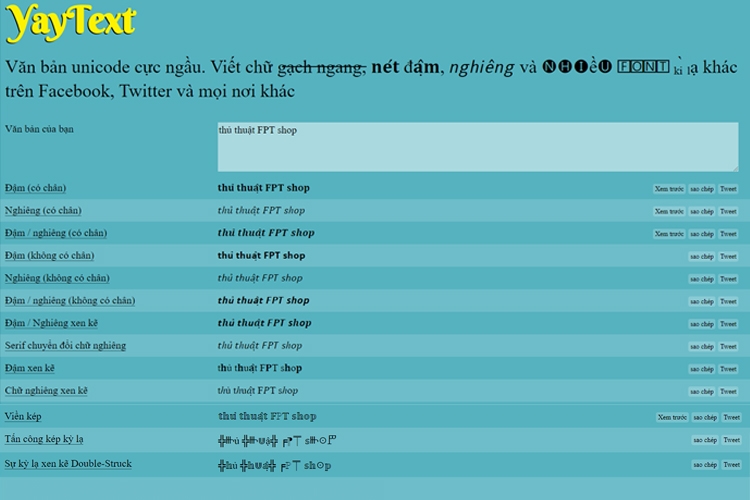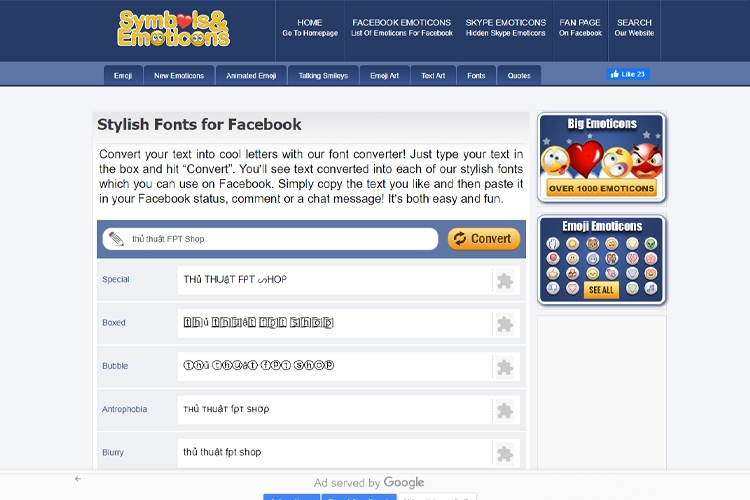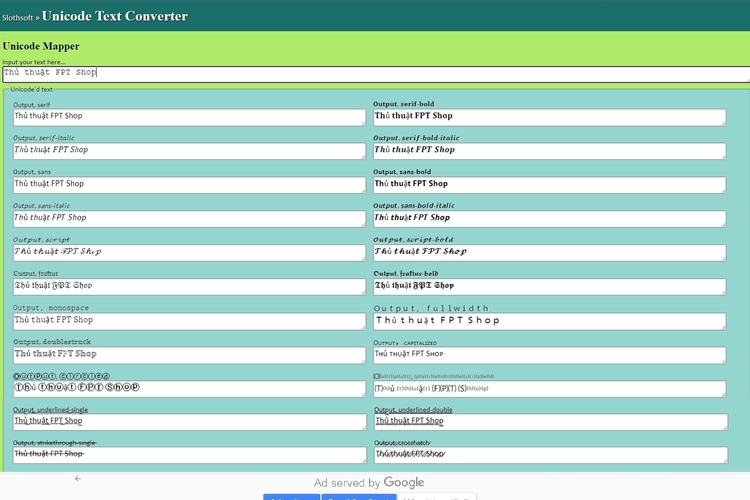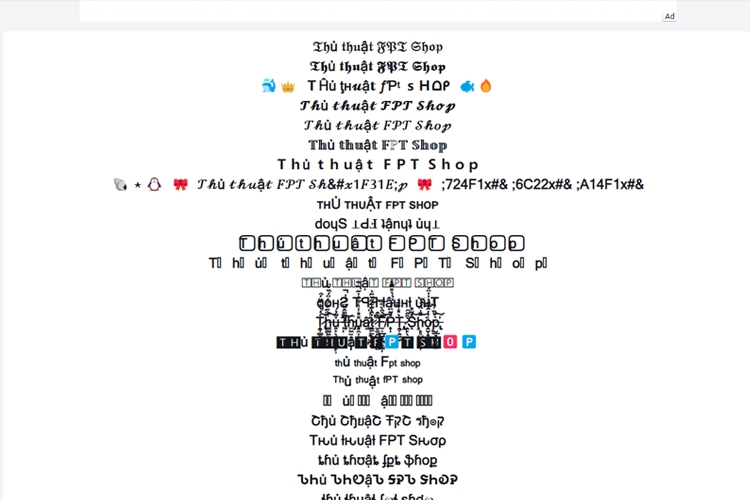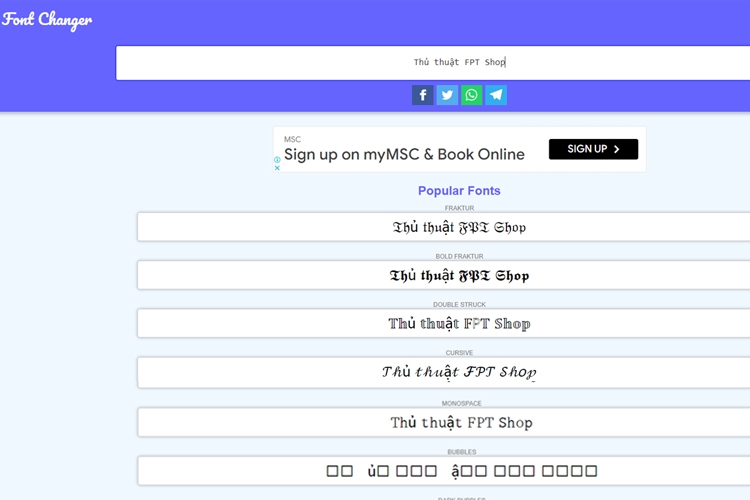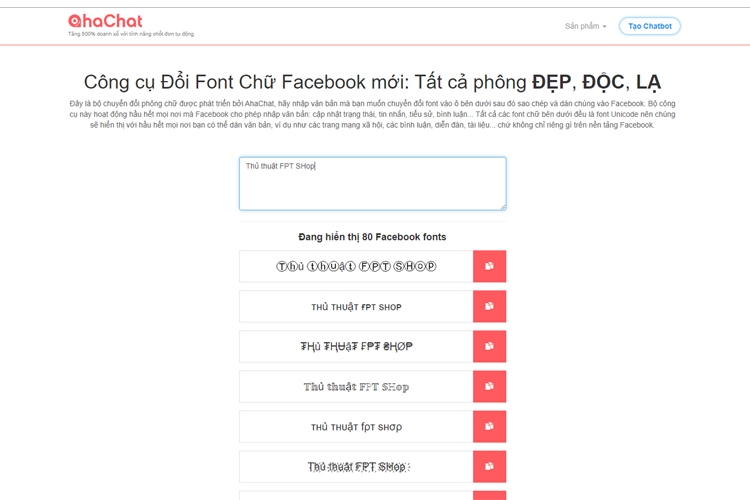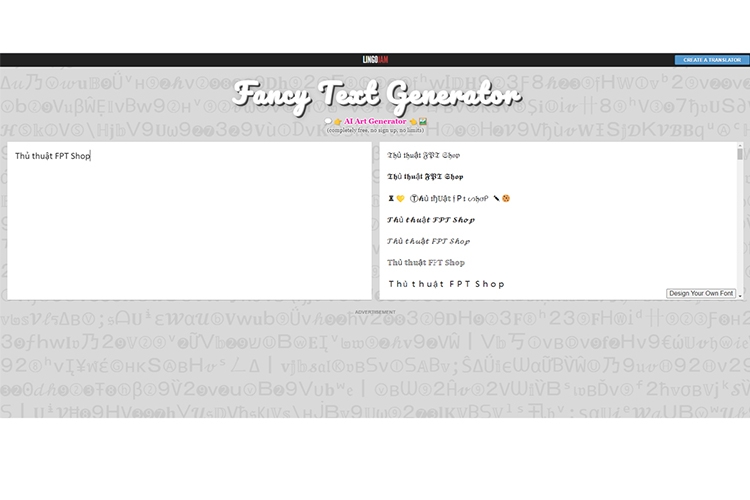
Hướng dẫn 7 cách đổi font chữ Facebook online đẹp độc đáo mà không cần tải phần mềm
Nếu bạn đang muốn đổi font chữ Facebook để tạo ấn tượng cho bài viết hơn thì hãy để FPT Shop giúp bạn. Trong bài viết dưới đây, FPT Shop sẽ mách bạn 7 cách đổi font chữ Facebook đơn giản nhé.
Facebook hiện là trang mạng xã hội lớn nhất thế giới với gần 3 tỷ người dùng và là trang mạng phổ biến nhất tại thị trường Việt Nam. Facebook cung cấp nhiều nội dung đa dạng giúp kết nối và chia sẻ những khoảnh khắc thường ngày. Cùng xem qua 7 cách đổi font chữ Facebook phổ biến nhất hiện nay nhé!
Lợi ích của việc đổi font chữ trên Facebook
Được phát triển như một trang mạng xã hội giúp chia sẻ và kết nối người dùng trên toàn cầu. Facebook ban đầu chỉ có tính năng chat, gọi thoại và đăng status kèm hình ảnh. Thế nhưng trải qua nhiều năm đột phá về công nghệ, nhu cầu của người dùng mỗi lúc một tăng lên, Facebook giờ đây đã có thêm các tính năng livestream, board game, đăng story và tạo avatar, quảng cáo, tạo reels,...
Chính vì vậy mà trang mạng xã hội này chưa bao giờ bị thụt lùi phía sau so với các đối thủ khác như Instagram, Twitter (X) và thậm chí là TikTok. Lượng người dùng Facebook nhiều nên việc tiếp cận khách hàng tiềm năng để quảng bá sản phẩm sẽ trở nên vô cùng dễ dàng. Và giữa vô vàn những đối thủ cạnh tranh khác, cách để thương hiệu của bạn trở nên nổi bật chính là phải có sự nổi bật về mặt hình ảnh và thông điệp. Những cách đổi font chữ Facebook độc đáo sẽ giúp bạn làm được điều đó.
Cách viết chữ in đậm/in nghiêng trong hội nhóm Facebook
Facebook rất thường xuyên update phần mềm trong khi người dùng lại dùng Unikey với các định dạng khác nhau. Điều này dễ dẫn đến sự xung đột font chữ Facebook do 2 phần mềm không tương thích. Hoặc trong vài trường hợp, bạn đang sử dụng một ứng dụng khác để thay đổi giao diện cho bàn phím điện thoại của mình và phần mềm này cũng tương thích được với Facebook App.
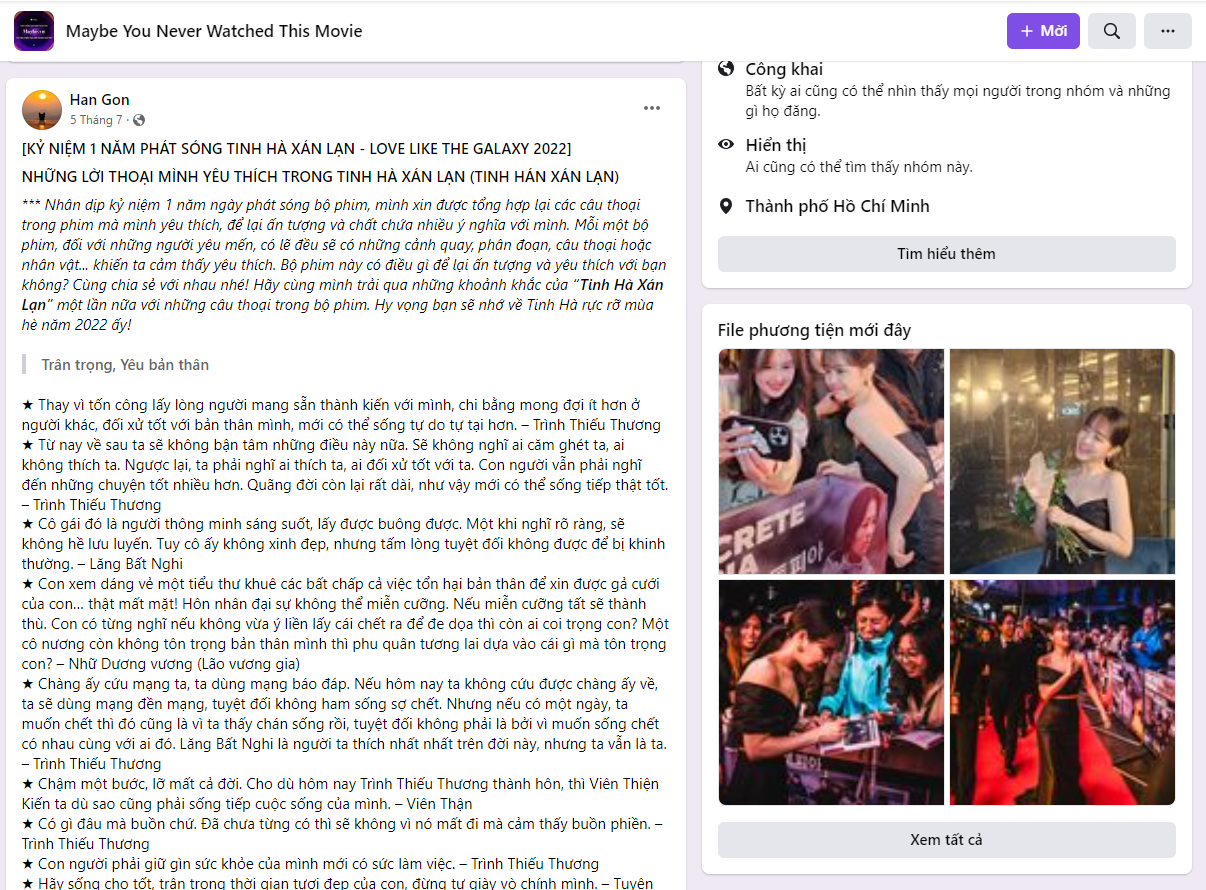
Hiện tại, Facebook chỉ có một số định dạng chữ đơn giản như chữ cam đỏ cho những cmt “Chúc mừng” hay chữ xanh dương cho những đường link, chữ xám trong ngoặc cho những trích dẫn… Một số kiểu chữ in đậm/in nghiêng đơn giản cũng có thể được thực hiện khi người dùng muốn đăng tải các bài viết trong group Facebook. Các phím tắt thực hiện như sau:
Bước 1: Bôi xanh văn bản muốn in đậm/in nghiêng
Bước 2: Chọn 1 trong 3 lệnh bên dưới để chuyển đổi định dạng văn bản
- Ctrl + B: In đậm
- Ctrl + I: In nghiêng
- Ctrl + U: Gạch dưới
Ngoài ra, để đăng được một bài viết có font chữ độc đáo theo ý muốn bên ngoài hội nhóm, người dùng phải sử dụng thêm phần mềm thứ ba là các trang web giúp đổi định dạng chữ.
Hướng dẫn 7 cách đổi font chữ Facebook online đẹp đơn giản
1. Cách đổi font chữ Facebook bằng Yaytext
Nhắc đến website cung cấp các font chữ độc đáo, Yaytext chắc chắn là cái tên được nghĩ đến đầu tiên với bất kỳ content writer nào. Giao diện dễ sử dụng, bạn có thể gõ chữ hoặc copy paste vào ô để đổi định dạng nhanh chóng. Yaytext có đủ các định dạng từ đơn giản như in đậm, in nghiêng, không chân, có chân cho đến các định dạng phức tạp như gạch chân, bong bóng, chèn icon,...
Để đổi font chữ bằng Yaytext, bạn chỉ cần làm theo những bước sau:
Bước 1: Truy cập vào website yaytext.com/vi/.
Bước 2: Bạn điền dòng chữ cần thay đổi định dạng vào ô trống “Văn bản của bạn”.
Bước 3: Sau khi điền xong, bạn sẽ thấy bên dưới đang hiển thị toàn bộ các lựa chọn font chữ đã được chuyển đổi. Bạn nhấn chọn sao chép để copy toàn bộ nội dung sau đó chuyển sang giao diện Facebook và nhấn paste/dán là được.
2. Đổi font chữ Facebook bằng Symbols & Emoticons
Khác với Yaytext chuyên cung cấp các định dạng cho các bài viết, Symbols & Emoticons nổi tiếng với những icon độc đáo. Font chữ của website này cũng tương đối đa dạng, đặc biệt với Special, Antrophobia và chữ gạch ngang. Symbols and Emoticons cũng chứa tất cả các icon trên Facebook và cung cấp các dạng Text Art (dạng text sử dụng các ký hiệu lặp đi lặp lại để tạo thành 1 bức tranh to lớn).
Bước 1: Bạn truy cập vào symbols-n-emoticons.com.
Bước 2: Phía trên có thanh menu ngang, bạn chọn tiếp “fonts”.
Bước 3: Điền văn bản cần chuyển đổi vào ô trống “Your text here” và ấn chọn Convert.
Bước 4: Nhấn giữ chuột trái để tô xanh lựa chọn font chữ mong muốn và nhấn chuột phải chọn copy.
3. Cách đổi font chữ Facebook bằng Slothsoft
Tương tự Yaytext, Slothsoft có giao diện đổi chữ tương đối dễ nhìn và có những font thông dụng nhất định.
Bước 1: Bạn truy cập vào slothsoft.net/UnicodeMapper/.
Bước 2: Điền văn bản cần chuyển đổi vào ô “Input your text here” trên cùng bên trái.
Bước 3: Kéo xuống dưới chọn mẫu ưng ý và tô xanh để sao chép.
4. Đổi font chữ FB bằng Fontvilla
Fontvilla có rất nhiều kiểu chữ khác nhau từ các font chuyên dụng để đăng bài content cho đến những font chữ cách điệu theo thế hệ trẻ gen Y, gen Z và cả chữ kèm icon. Điểm trừ duy nhất của website này chính là thời gian tải trang khá lâu và các font chữ hiển thị bên dưới xếp chồng lên nhau khó nhìn.
Bước 1: Bạn truy cập vào website fontvilla.com.
Bước 2: Điền văn bản cần chuyển đổi vào ô “Paste/Type your text here”.
Bước 3: Kéo xuống dưới và tô xanh font chữ mong muốn, sau đó nhấn chuột phải chọn sao chép.
.jpg)
5. Đổi font chữ Facebook bằng Font Changer
Sử dụng Font Changer như một thủ thuật đơn giản để đổi font chữ Facebook. Website này được phát triển bởi Lingo Jam và có đến hơn 50 kiểu chữ khác nhau cho bạn tha hồ lựa chọn. Font Changer rất thường xuyên làm mới nên thường có những font chữ mới lạ so với các website khác.
Bước 1: Truy cập vào fontchanger.net.
Bước 2: Nhập văn bản muốn chuyển đổi vào khung “Normal text”.
Bước 3: Các lựa chọn font chữ sẽ hiển thị bên dưới, bạn chỉ cần ấn vào lựa chọn mong muốn là website đã tự động copy vào bộ nhớ đệm. Sau đó bạn chuyển sang Facebook và nhấn paste/dán.
.jpg)
6. Cách đổi font chữ Facebook bằng AhaChat
Ahachat là 1 website chuyên cung cấp các giải pháp chatbot, tăng tương tác Marketing cho doanh nghiệp. Ngoài ra, website này còn có hơn 80 font chữ đẹp độc đáo để bạn sử dụng trên Facebook.
Bước 1: Truy cập vào website ahachat.com/facebook-text.
Bước 2: Nhập văn bản cần chuyển đổi vào khung “some preview text”.
Bước 3: Phía dưới sẽ hiển thị 80 kiểu font Facebook thông dụng. Click vào biểu tượng sao chép màu đỏ để copy kiểu chữ yêu thích và dán vào Facebook.
.jpg)
7. Sử dụng LingoJam để đổi font chữ FB
Với khẩu hiệu “no limits”, LingoJam là một website chuyên cung cấp những font chữ độc đáo và gần như là tổng hợp từ những website khác nhau. Tại LingoJam, bạn có thể tìm thấy các font chữ đơn giản như tô đậm, in nghiêng, gạch chân, gạch ngang phù hợp cho các bài content trang trọng. Cho đến những kiểu chữ kèm icon, cách điệu theo ngôn ngữ gen Y, gen Z.
Ngoài những font chữ sẵn có, bạn còn có thể tự tạo font chữ của riêng mình bằng cách nhấn vào ô “Design your own font” bên phải màn hình. Tại đây bạn có thể chọn thay đổi font khác nhau của 26 chữ cái tuỳ ý để ra được một văn bản hoàn chỉnh.
Bước 1: Truy cập vào website lingojam.com/FancyTextGenerator.
Bước 2: Nhập văn bản mà bạn muốn chuyển đổi vào ô “Normal text goes here…” ở bên trái màn hình.
Bước 3: Các thay đổi font chữ sẽ hiển thị ở khung bên phải màn hình, bạn kéo thanh trượt lên xuống để xem toàn bộ. Nếu ưng ý với font chữ nào, nhấn giữ chuột để bôi xanh và chọn copy sau đó dán vào Facebook.